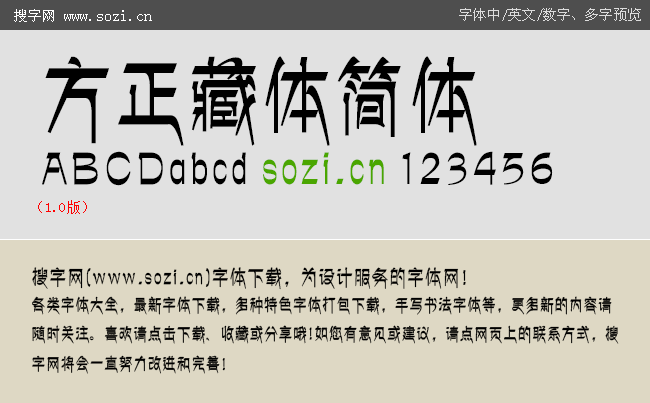
方正藏體簡體(方正藏體簡體 方正藏意漢體)
搜字網(wǎng)提供一款方正藏體簡體下載。方正藏體簡體是一款根據(jù)藏文風(fēng)格設(shè)計(jì)的中文藝術(shù)字體。風(fēng)格獨(dú)特,極具個(gè)性,適合電影海報(bào)、畫冊(cè)設(shè)計(jì)、包裝設(shè)計(jì)等廣告設(shè)計(jì)使用。